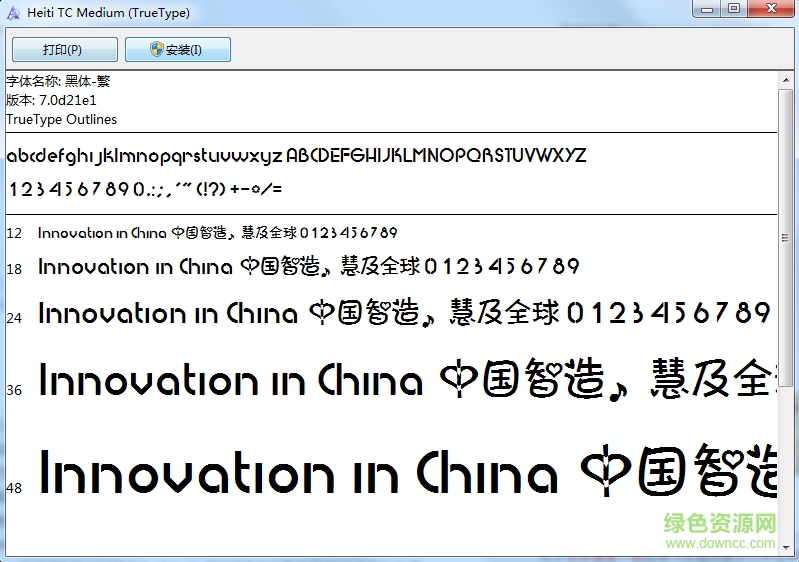
小清新字体是一款充满了各种心形造像和音符点缀的艺术字体,让你的文字显得更为轻松活泼,支持繁体中文输入,黑体模板更显大方抢眼,绿色资源网诚意推荐!
小清新中文字体是一款可爱心形小清新中文字体本作品可用于广告设计字体、网页设计字体、包装设计字体、屏幕显示字体等。
小清新中文字体采用了心形和音符来修饰文字,在字里行间显得活泼生动,满足你的小清新个性,可用于多种场合,欢迎免费尝试哦!商务使用还请去官网授权哦!